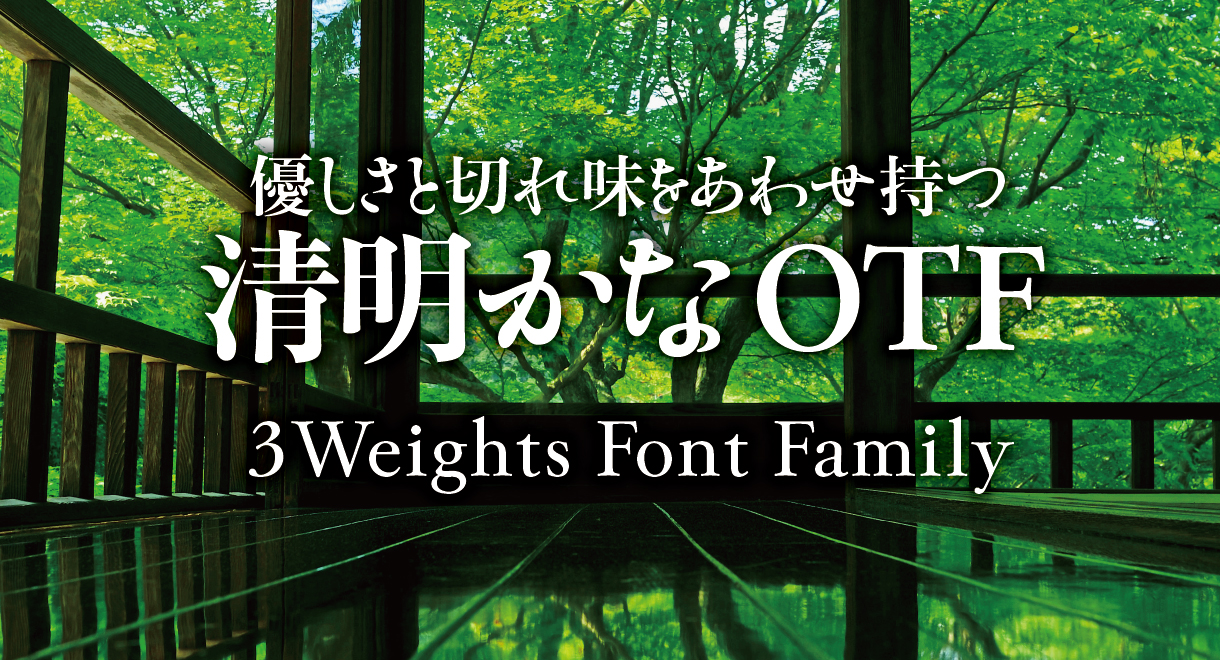
米国 Monotype Imaging Inc.の日本法人Monotype株式会社(東京都港区、以下 Monotype)は、Monotypeの提供するフォントサービス「Monotype Fonts」「MyFonts」「フォントワークス LETS」「FONTPLUS」にREN FONTの92書体を搭載しました。また、日本タイポグラフィ協会主催の作品展「年鑑2026」で「清明かな・余韻かな」が入選しました。
「和音 Pro」
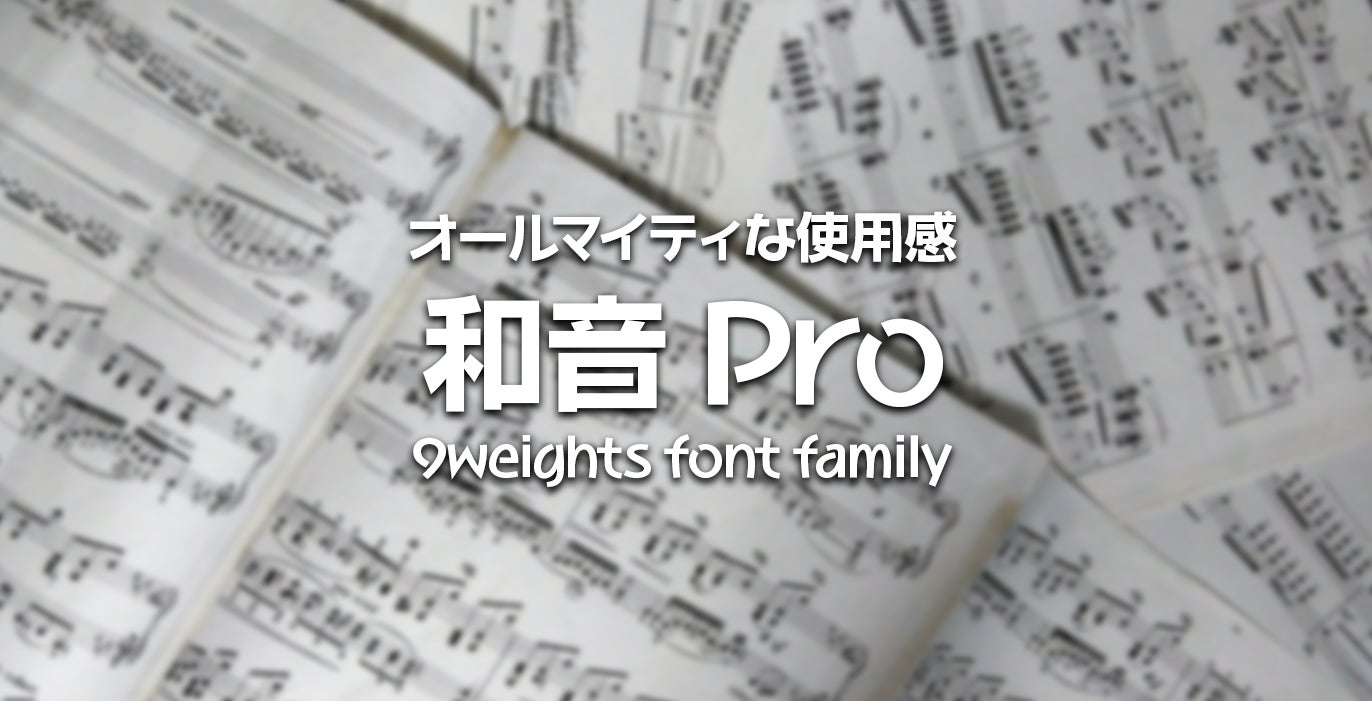
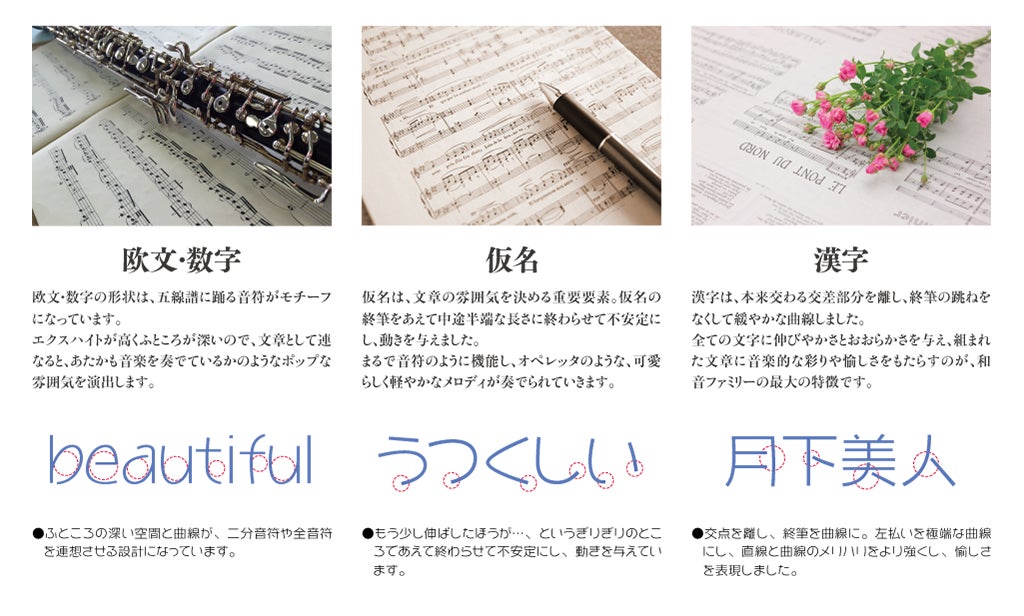
「清流かなOTF」
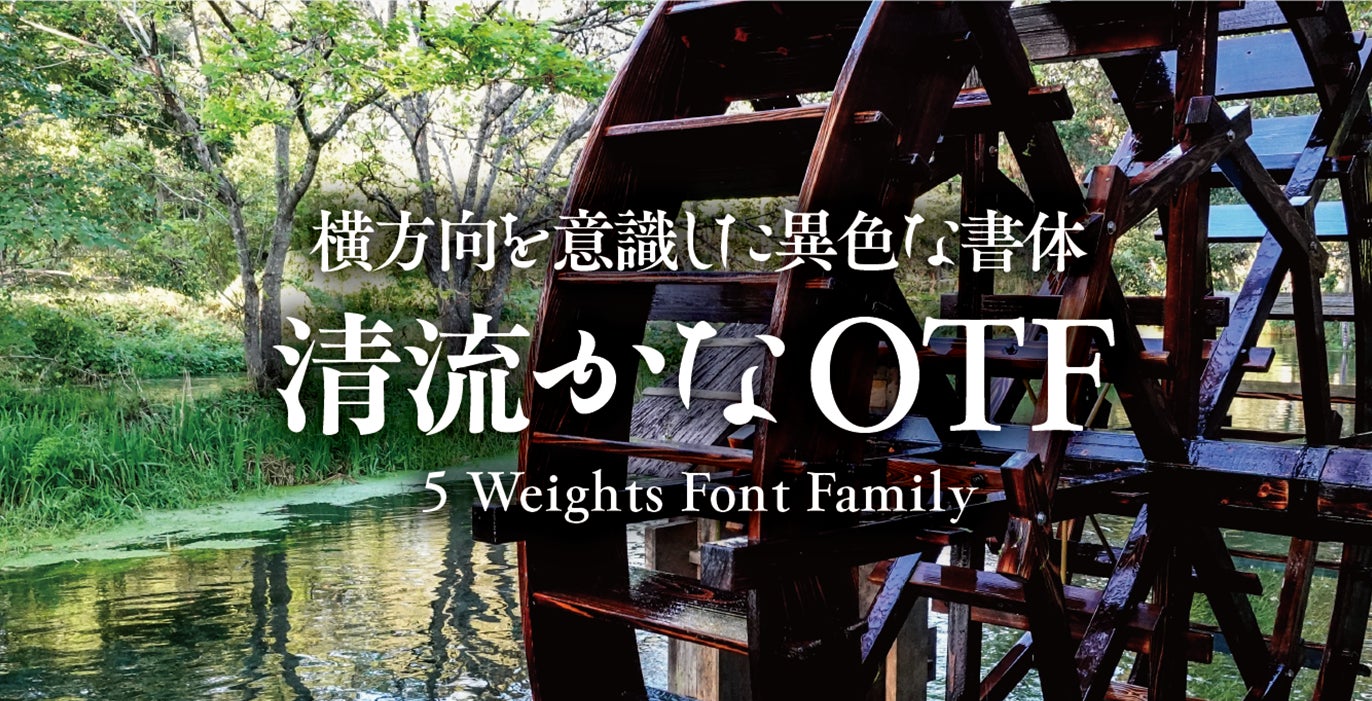
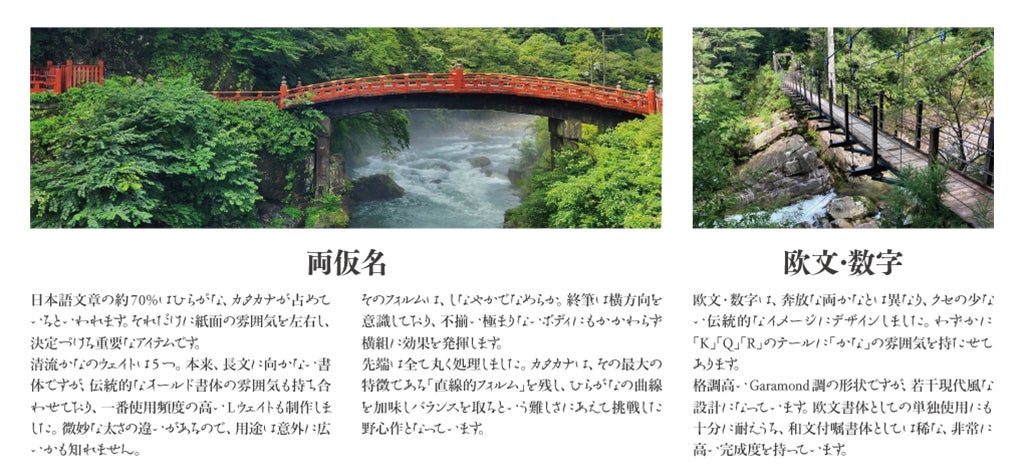
「ほんまるかな」
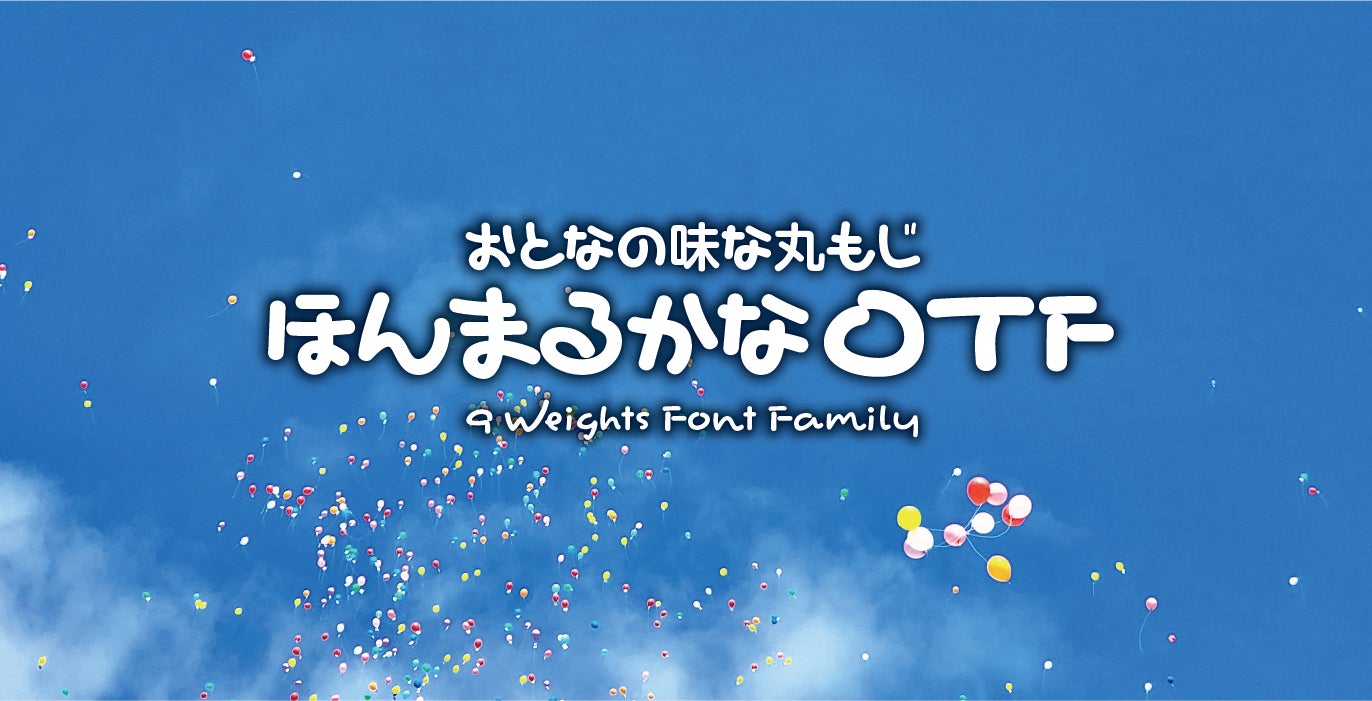
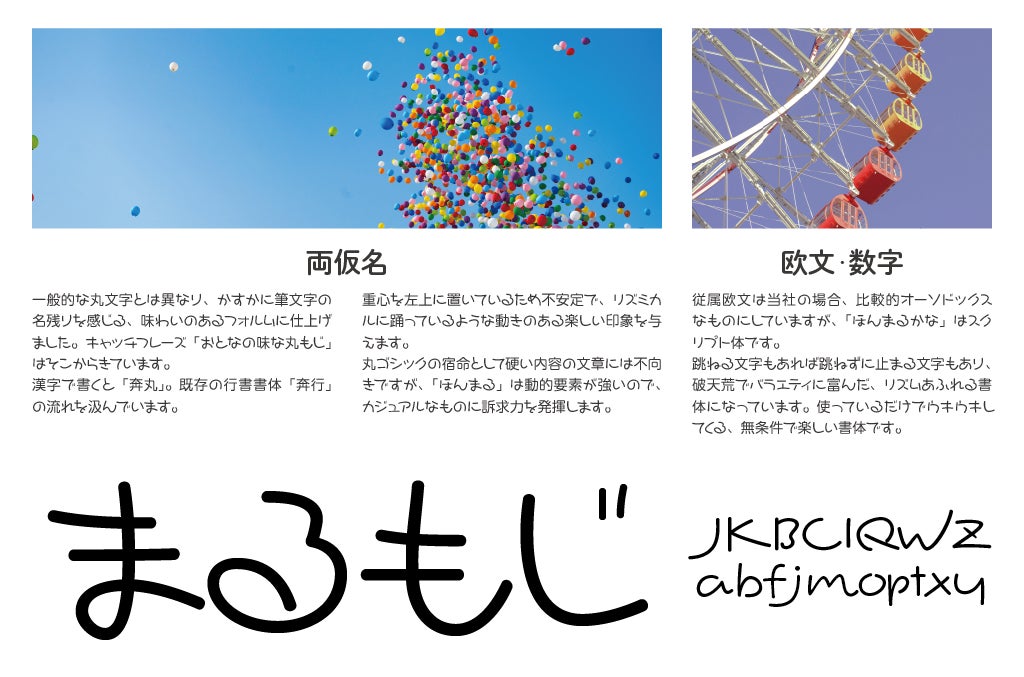
「奔行2かな」
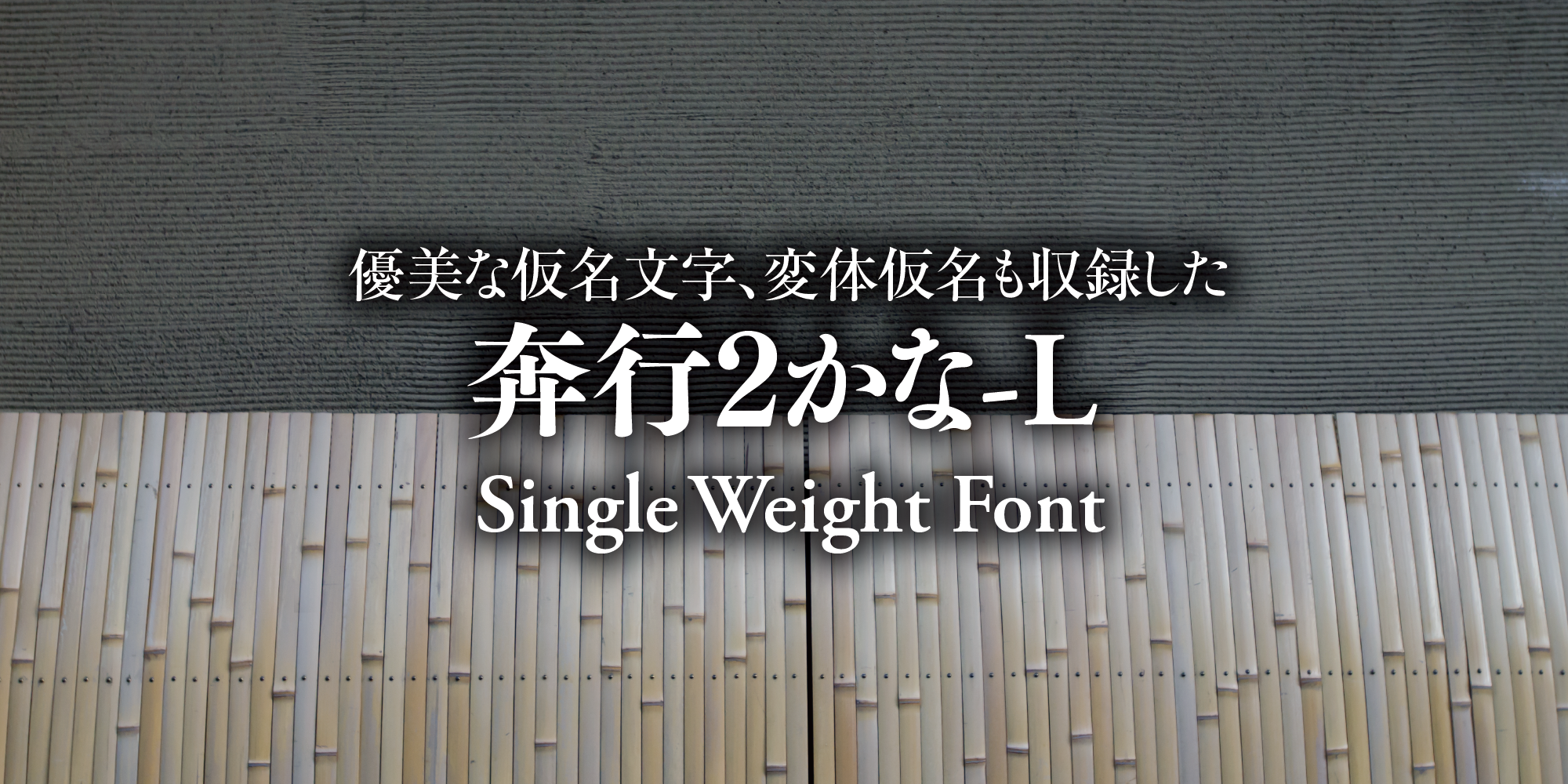
優美な仮名文字、変体仮名も収録
奔行2かな-Lは、特定非営利活動法人日本タイポグラフィ協会により開催された、2004年度「日本タイポグラフィ年鑑2004」コンテストの書体部門入選作「勢蓮奔行-L」を源流とし、制作されています。
平仮名、片仮名、欧文、記号類、変体仮名の各字種を収録し、楷書から行書へ崩す書法の中間レベルの筆致を全文字で展開、書の奔放さを表現しました。 また、変体仮名は、現代仮名各文字に対応する異体字として容易に呼び出すことができます。さらに、Unicode(一部文字種)にも対応しました。この変体仮名は現代仮名と違和感の少ない整形を施しており、新旧かなの混在ができる、独創的な書体となっています。
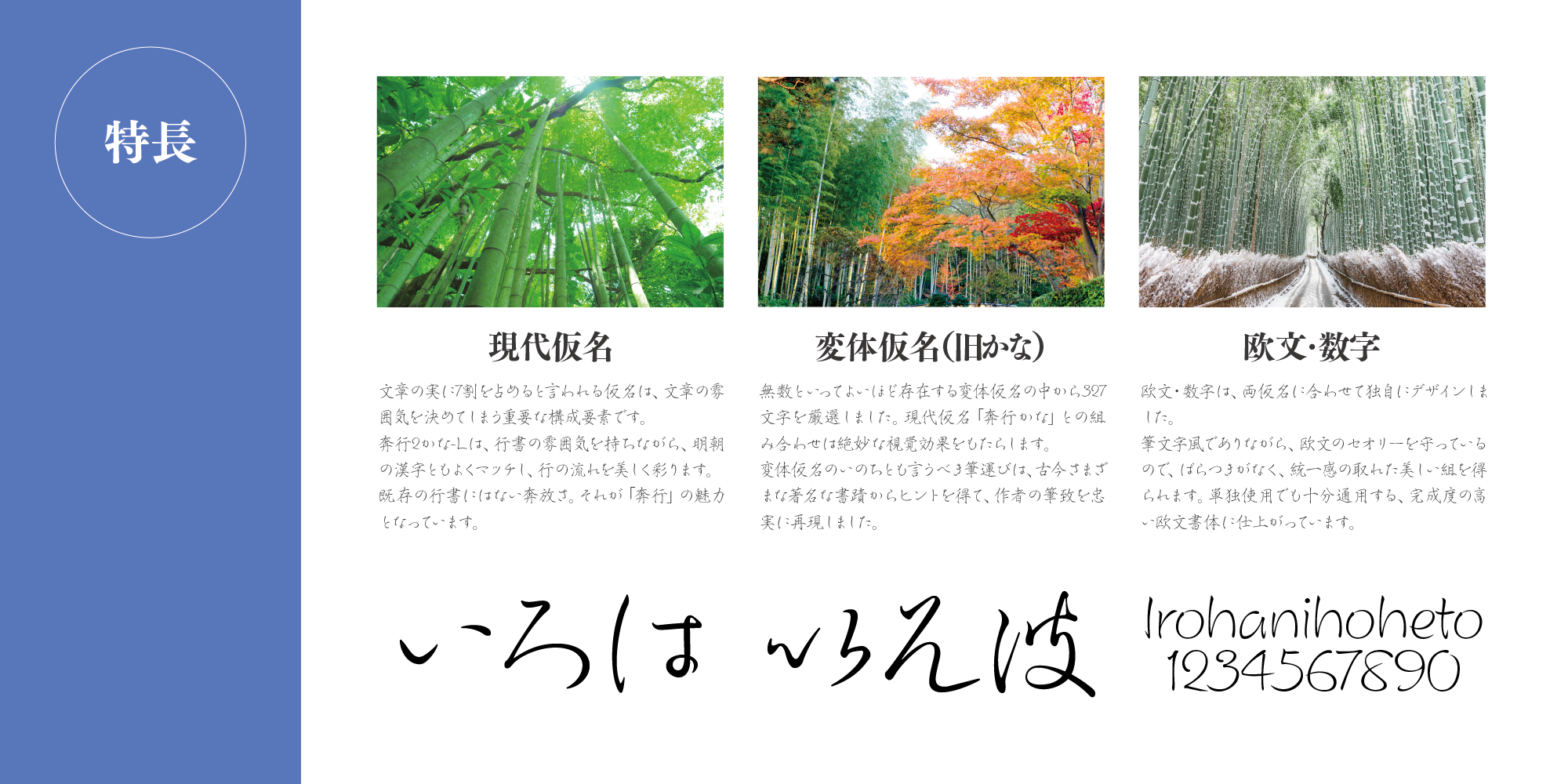
奔行2かなには拗音・促音・濁音および「ん」以外の全ての各現代仮名の「音」に対応した変体仮名が327文字追加装備されております。変体仮名のUnicode対応、横組み・縦組みにプロポーショナル・ペアカーニング処理など、機能を充実しました。なお「奔行かなStd-L」との互換性はありません。
「Festoso」
Festoso はイタリア語の音楽用語で、「陽気な」「楽しい」といった意味があります。音楽においては、演奏を陽気に、お祭りのように明るく行うよう指示する際に使われる表現です。
この書体 Festoso も、まさにそのお祭りのような陽気さを表現しています。跳ねる文字もあれば、ピタッと止まる文字もあり、予測不可能でバラエティに富んだ、リズム感あふれる破天荒なデザインです。使っているだけで気分が高まり、無条件に楽しくなってくるフォントです。